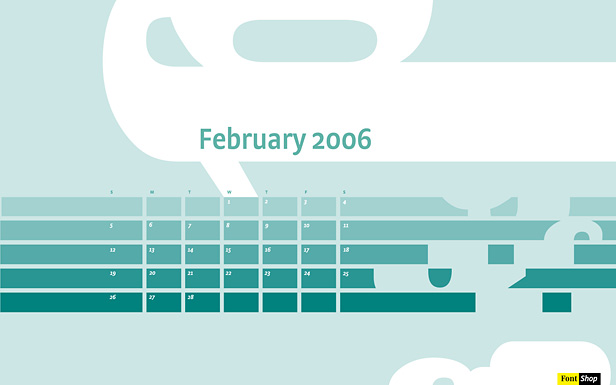
Noch mehr
Bildschirmhintergründe als im Januar: unser
typografisches Februar-Blatt, gestaltet in der
FF Strada von
Albert Pinggera ...
Februar-Blatt wieder ein kleiner Hinweis, welche
Schrift uns im kommenden Monat erfreuen wird.
Für die Gestaltung des Januar-Kalenderblattes griffen unsere Gestalter zur Schrift FF Strada aus der FontFont-Bibliothek. Albert Pinggera entwarf die ersten Schnitte dieser Schrift noch während seines Studiums in Den Haag. Als Ausgangsbasis dienten ihm in Stein gemeißelte Kurven, aus denen er zunächst den kursiven Schnitt herleitete. In den darauf folgenden Jahren entstand eine sehr gut lesbare Sans Serif mit geringem Kontrast und außergewöhnlichen Formen in den Display-Größen. FF Strada wurde 2003 vom Type Directors Club ausgezeichnet. Mehr über die Schrift in einer kostenlosen FontFont-Focus-Broschüre.*
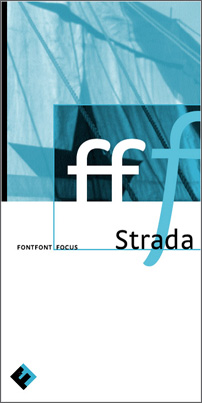
Die Geschichte von FF Strada, in der kostenlosen FontFont-Focus-Broschüre (per Mail bestellen)
heute morgen nicht beantworten, aber ein paar
Spekulationen in die Welt setzen.
Vielleicht hat es mit der handwerklichen Herkunft des Formulierung zu tun. So wie man Statuen aus Marmor fertigt, so hat man im Bleisatz Texte aus der Garamond gesetzt.
Foto: Photodisc; mehr ...
Für uns Digitalkinder ist Schrift zur virtuellen Masse geworden, so wie Farben und Töne: ein Buchumschlag in blau oder eine Symphonie in C-Dur. Also: gesetzt in Garamond.
Wer widerspricht?
Foto: Fancy, mehr ...
Bilder aus der Frühzeit des Fußballs
Die
Foto-Wanderausstellung »Faszination Fußball«
Mit der SZ-Bibliothek (links) begann vor 3 Jahren die Erfolgsgeschichte der Süddeutsche-Zeitung-Edition; es folgte die DVD-Serie (beide gestaltet mit FF Meta), die Kinderbuchserie (FF Erikrighthand) und jetzt die Kriminalbibliothek (FF Trixie)